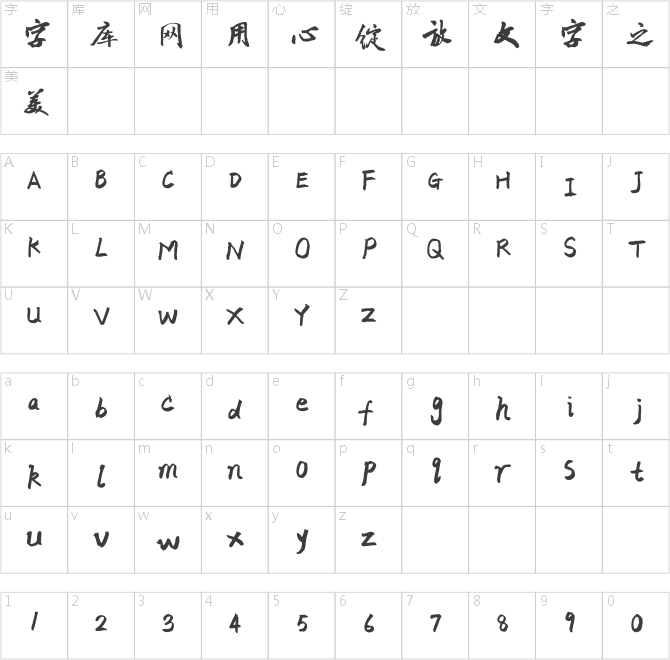
桃煦古風(fēng)廣告簡體 詳情頁
《桃煦古風(fēng)廣告簡體》是一款適合視頻制作、平臺設(shè)計(jì)和辦公文稿的毛筆字體。該字體適全當(dāng)今 時代閱讀和審美要求,在學(xué)習(xí)和傳承中國書法,充分發(fā)揮電腦等現(xiàn)代信息技術(shù)優(yōu)勢,將古風(fēng)古韻融入現(xiàn)代廣告字體,整理形成的一套適應(yīng)視頻制作、平面設(shè)計(jì)和電腦方案起草的字體。主要特色如下:
一、具有古風(fēng)古韻。充分汲取中國5000多年書法豐富的營養(yǎng),盡力展現(xiàn)古人筆法、結(jié)字和墨色,發(fā)揮毛筆豐富的點(diǎn)畫、線條表現(xiàn)特色,使字體具體較強(qiáng)的古風(fēng)古韻。
二、適應(yīng)現(xiàn)代審美。緊跟當(dāng)今時代時代發(fā)展趨勢,適應(yīng)現(xiàn)代信息對廣告、美術(shù)等字體的需求,注重使用簡體字規(guī)范字,避免個別讀者辨認(rèn)繁體字費(fèi)時,日漸生疏的困惑。
三、較強(qiáng)使用場景。不僅是電腦上視頻制作、平臺設(shè)計(jì)和文稿處理的PC字庫,而可適用于手機(jī)和平版等電子產(chǎn)品,能夠在多種場景使用和運(yùn)用。